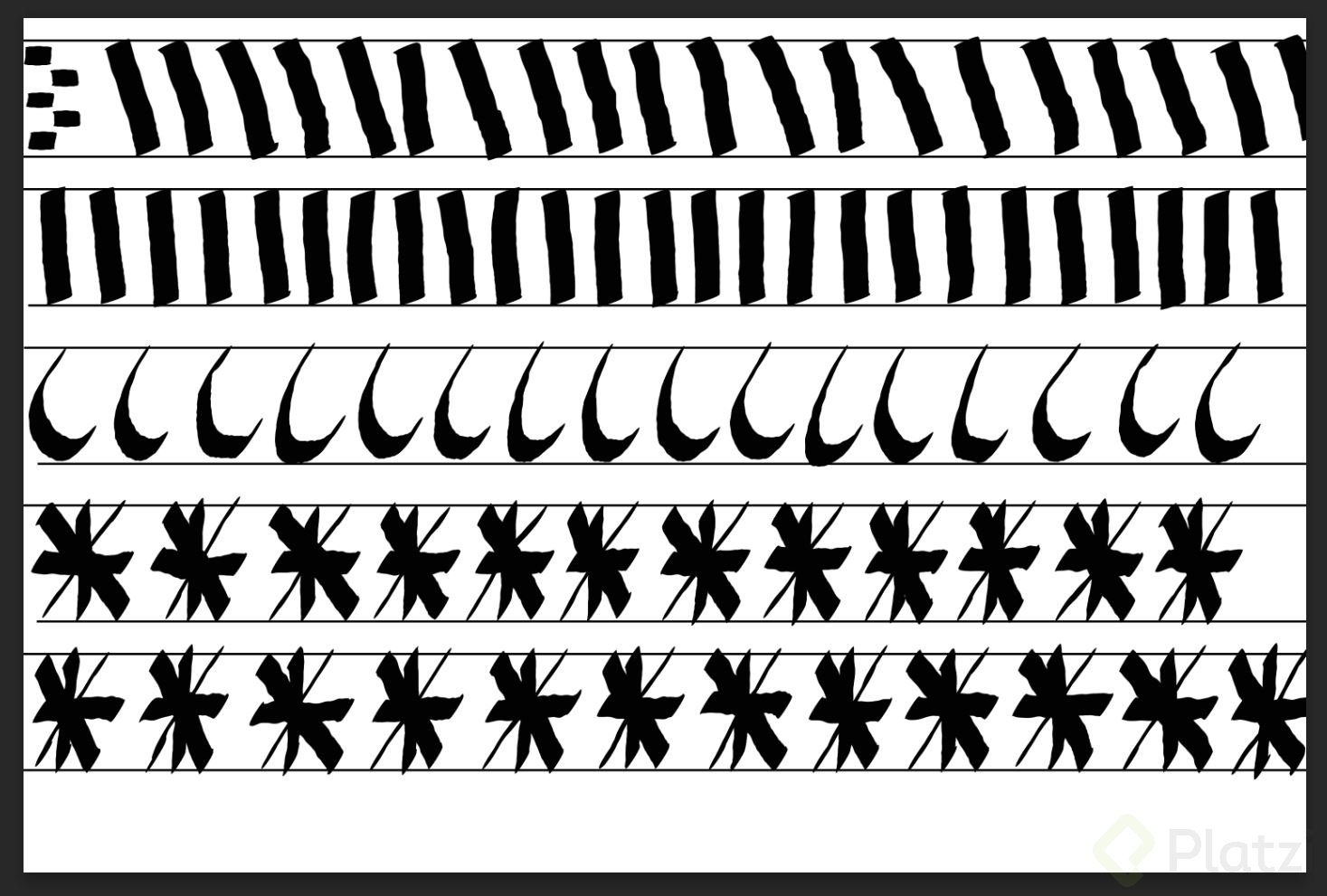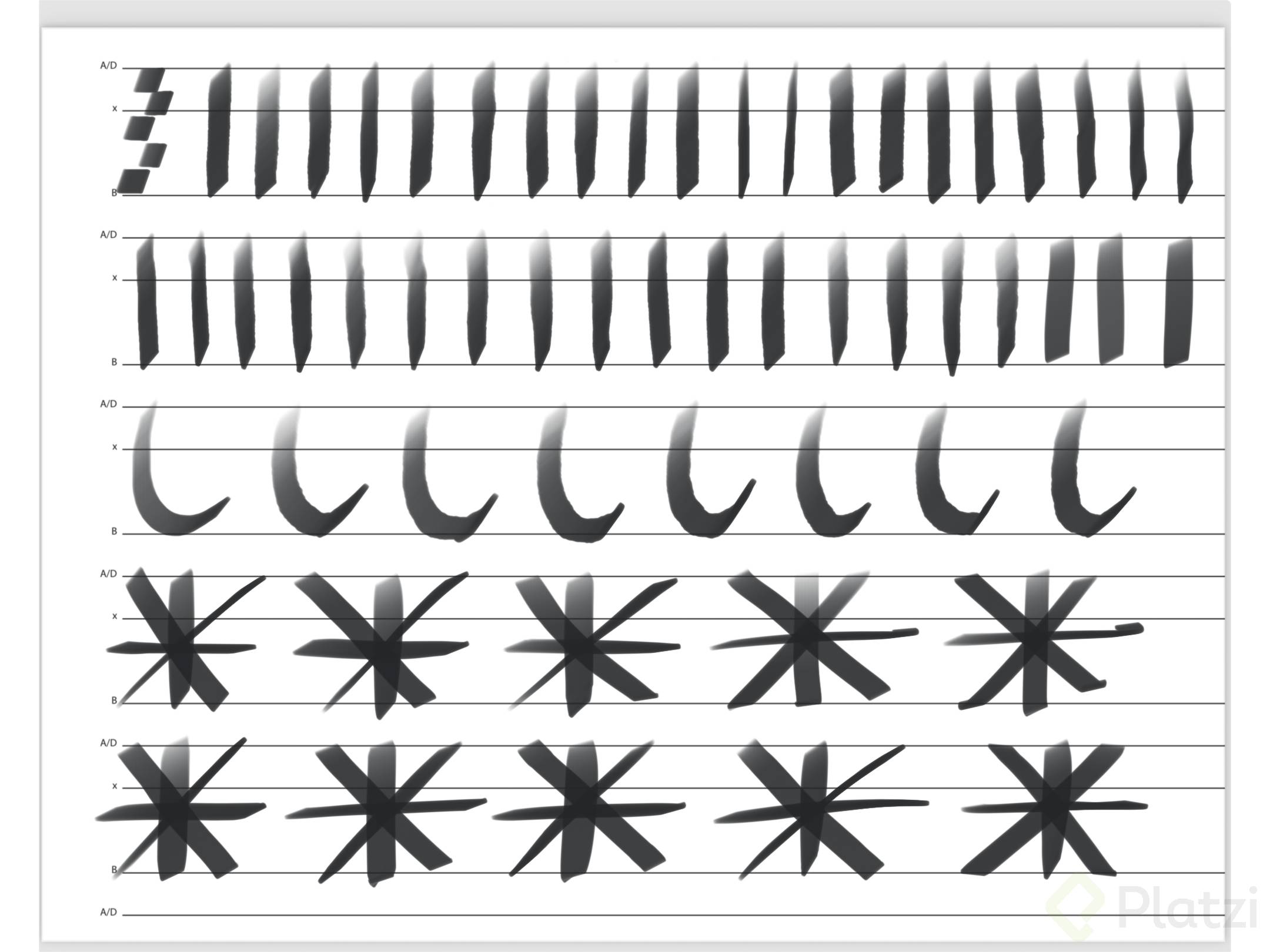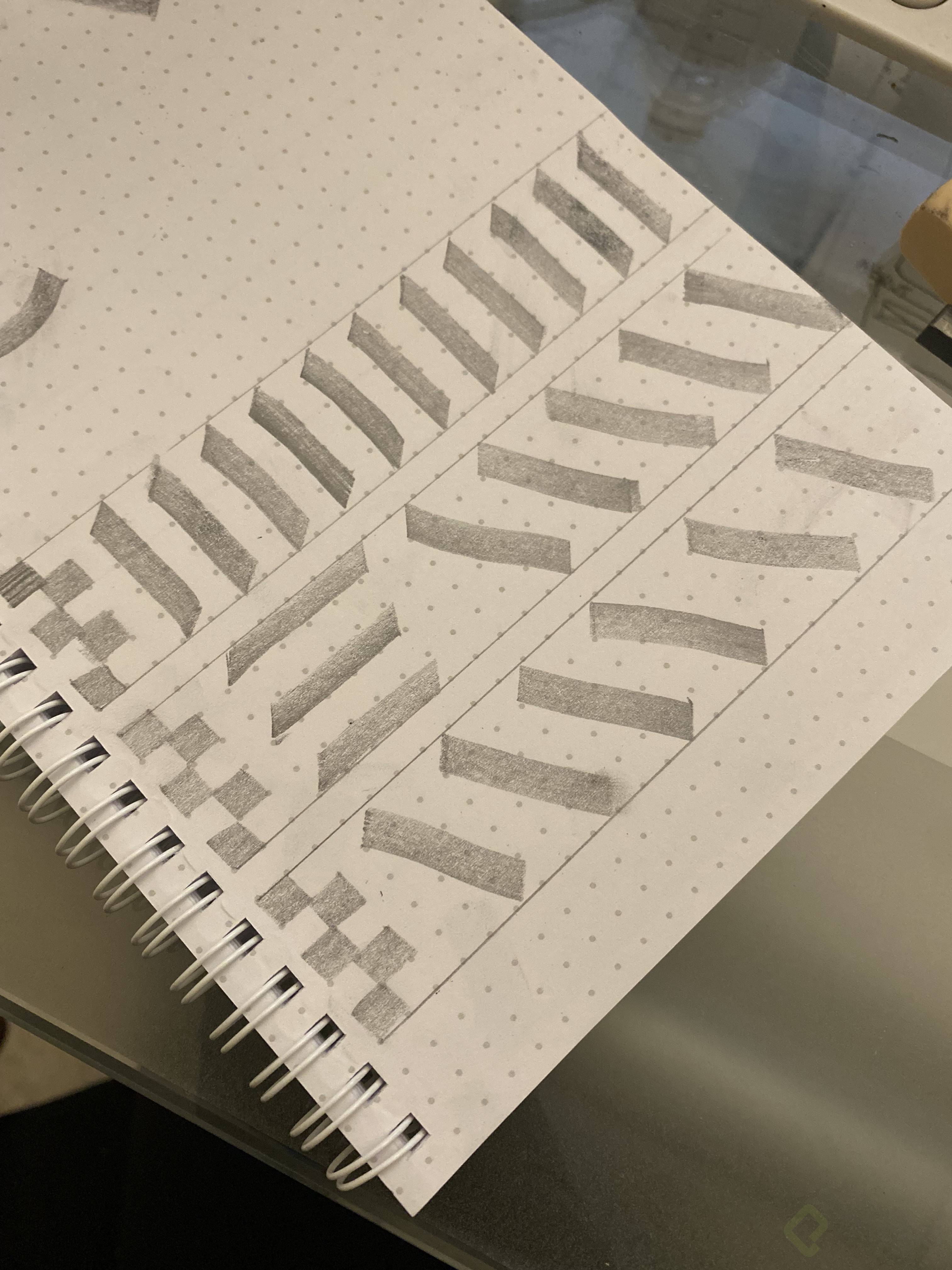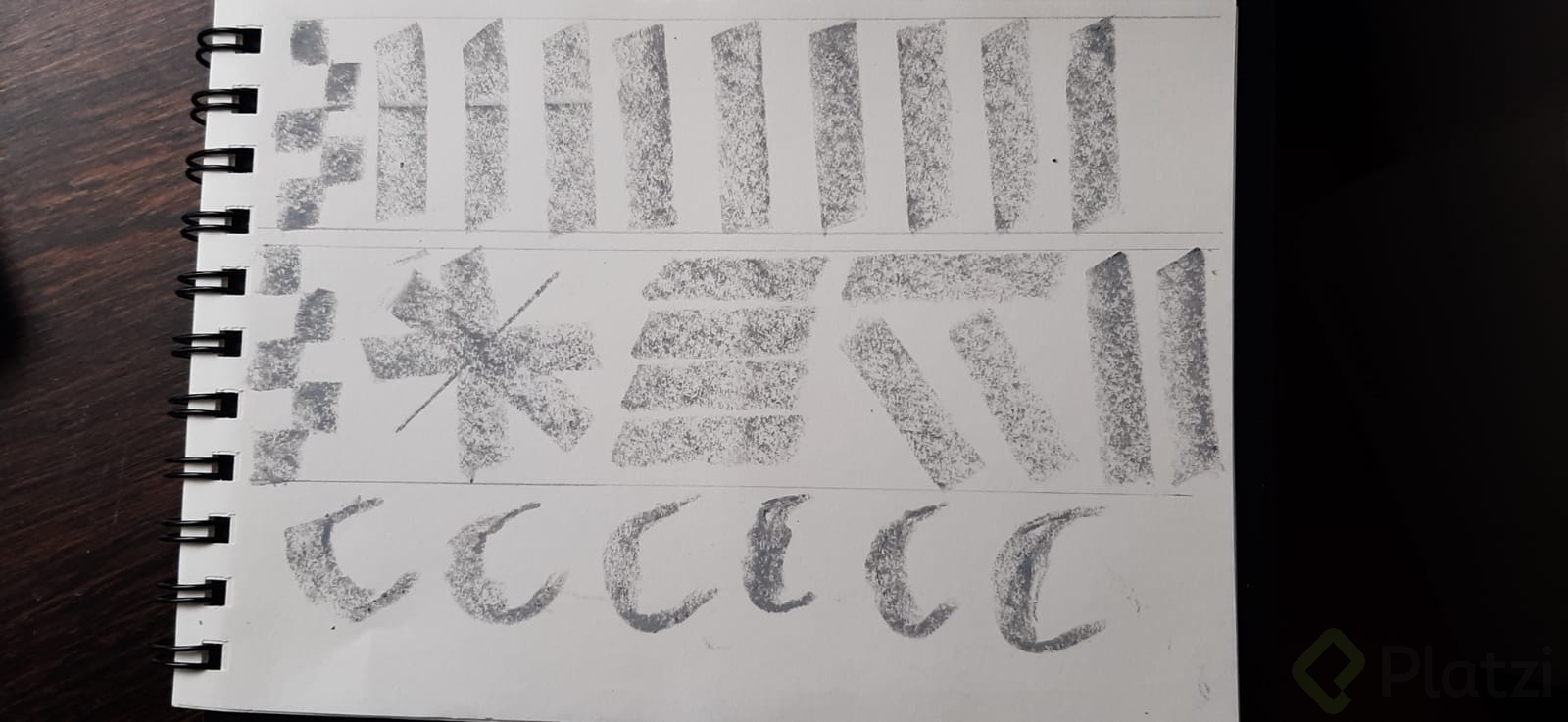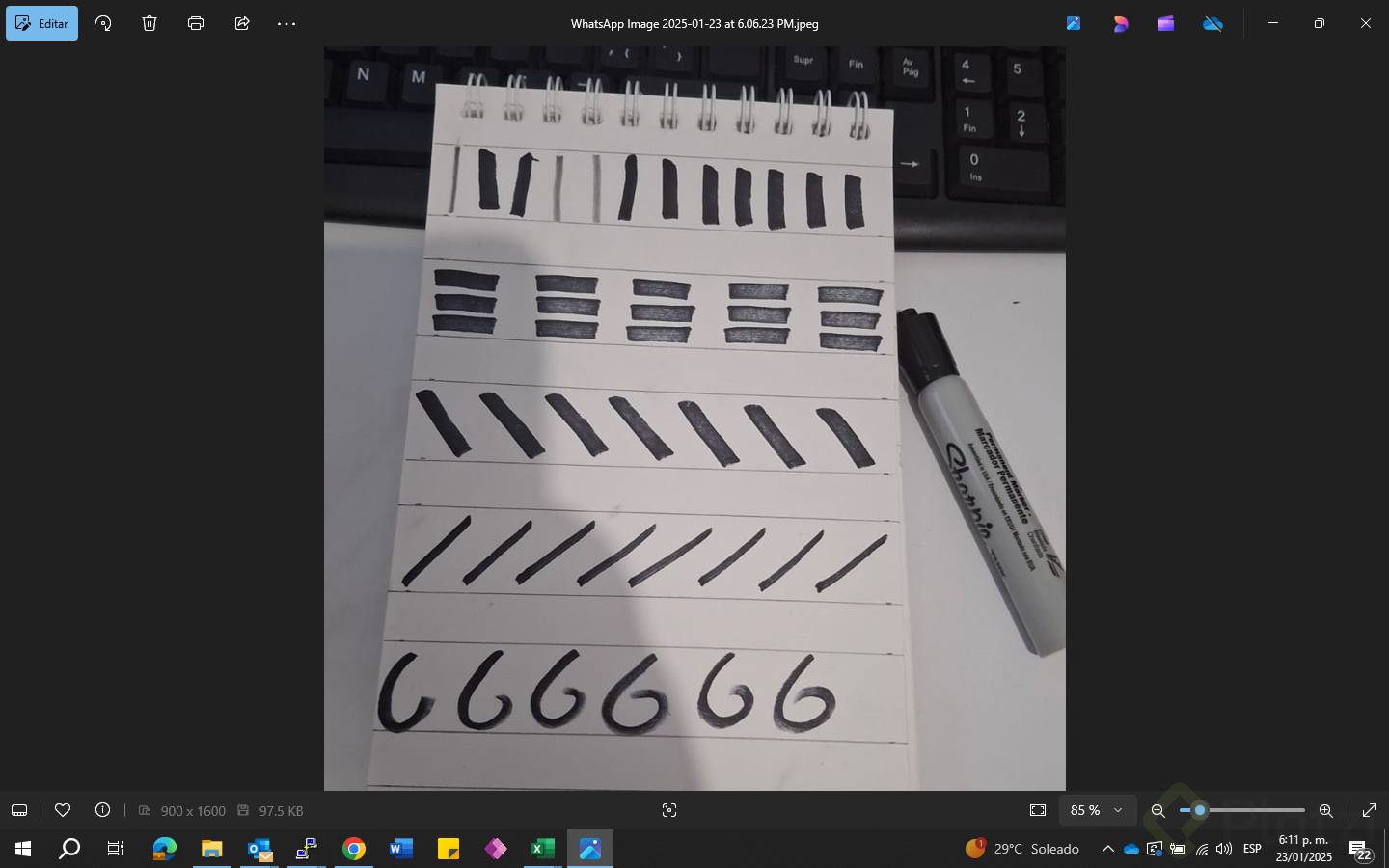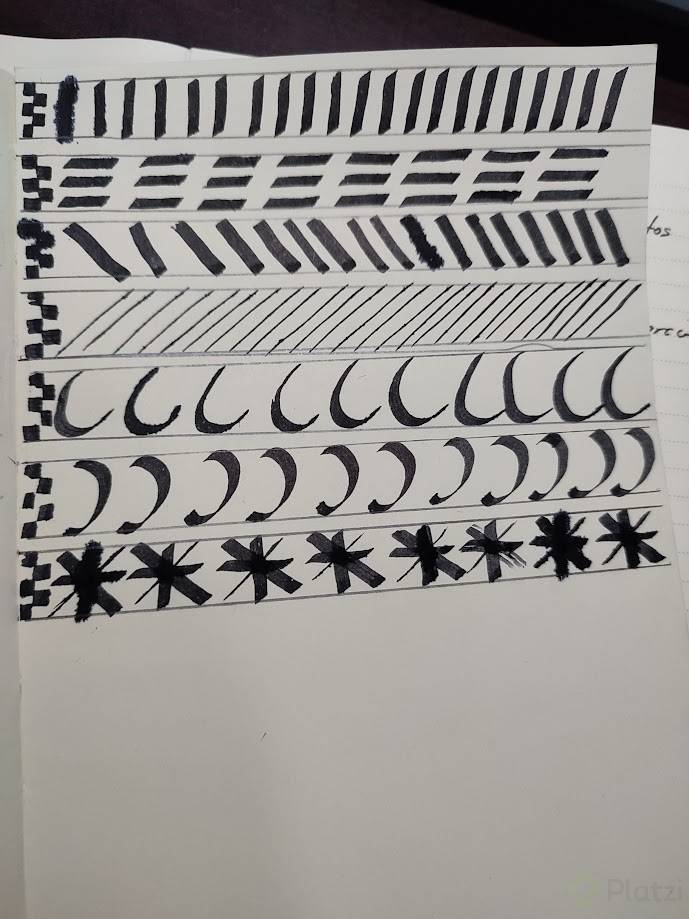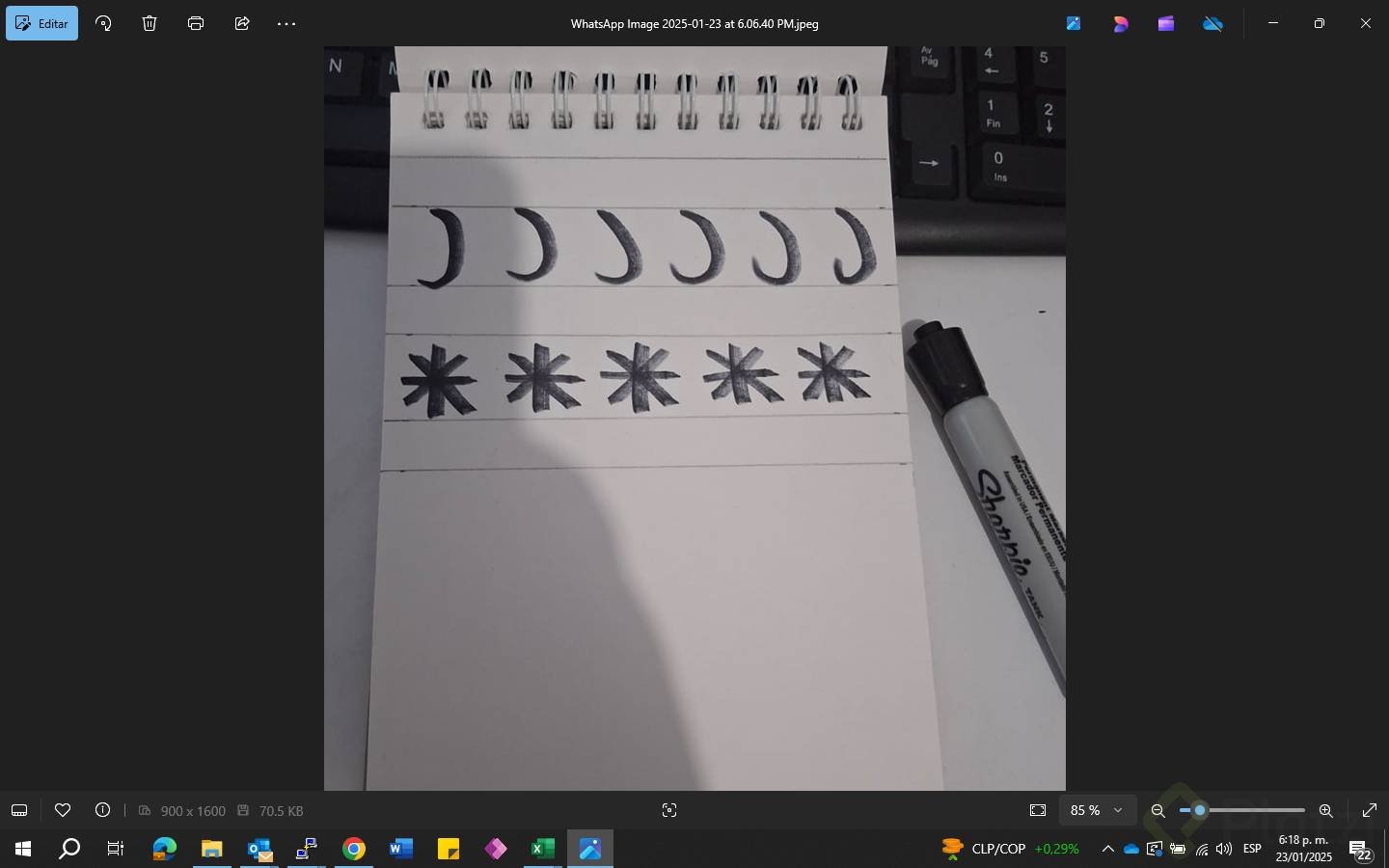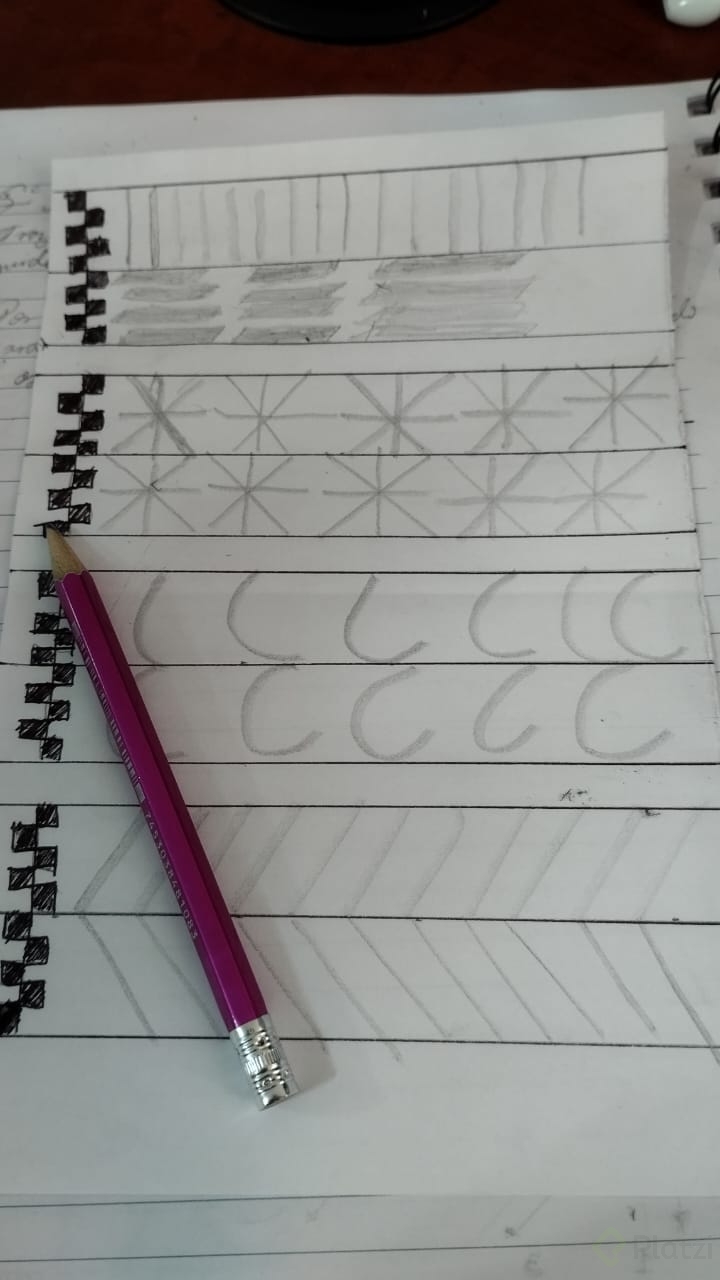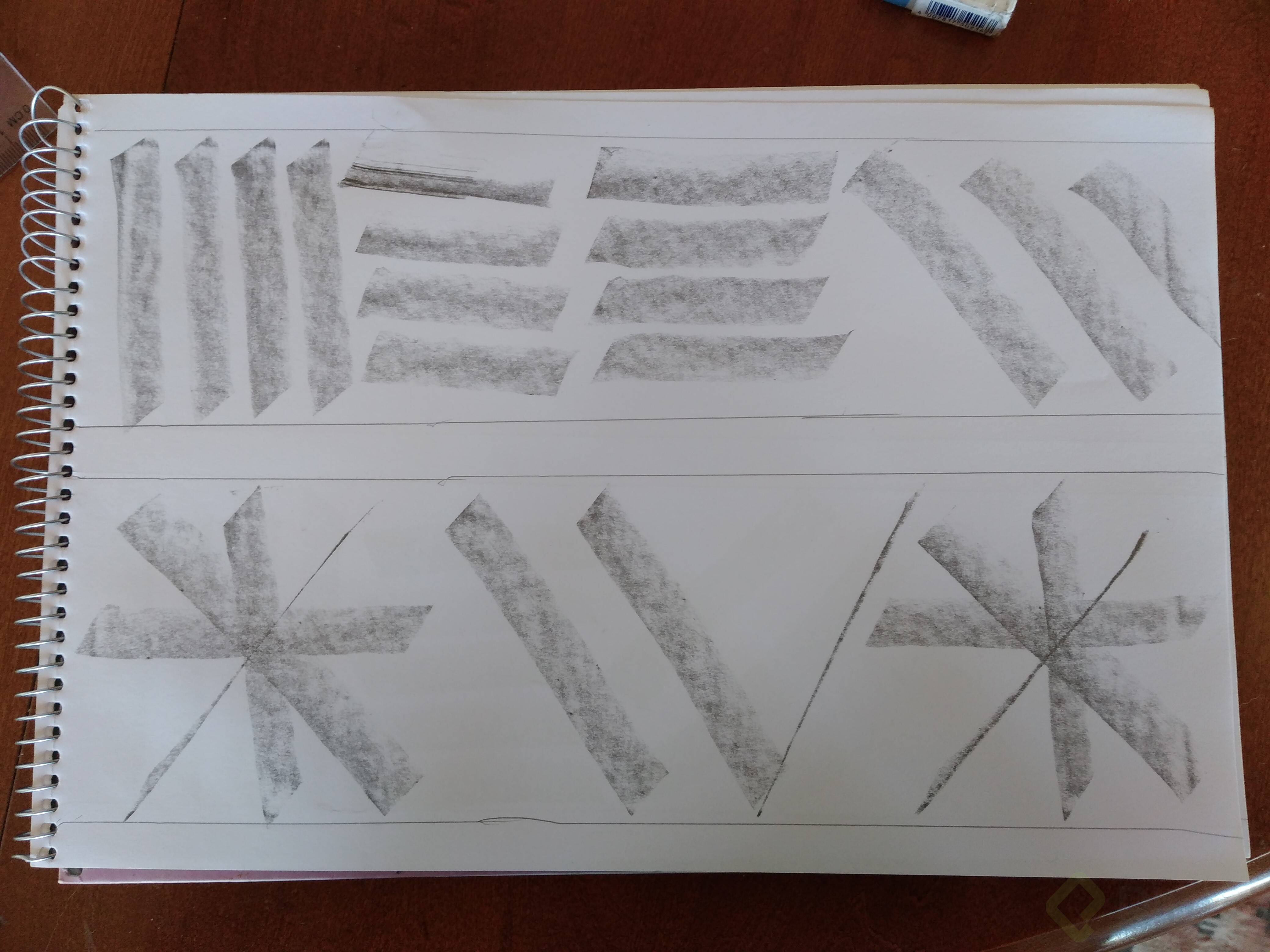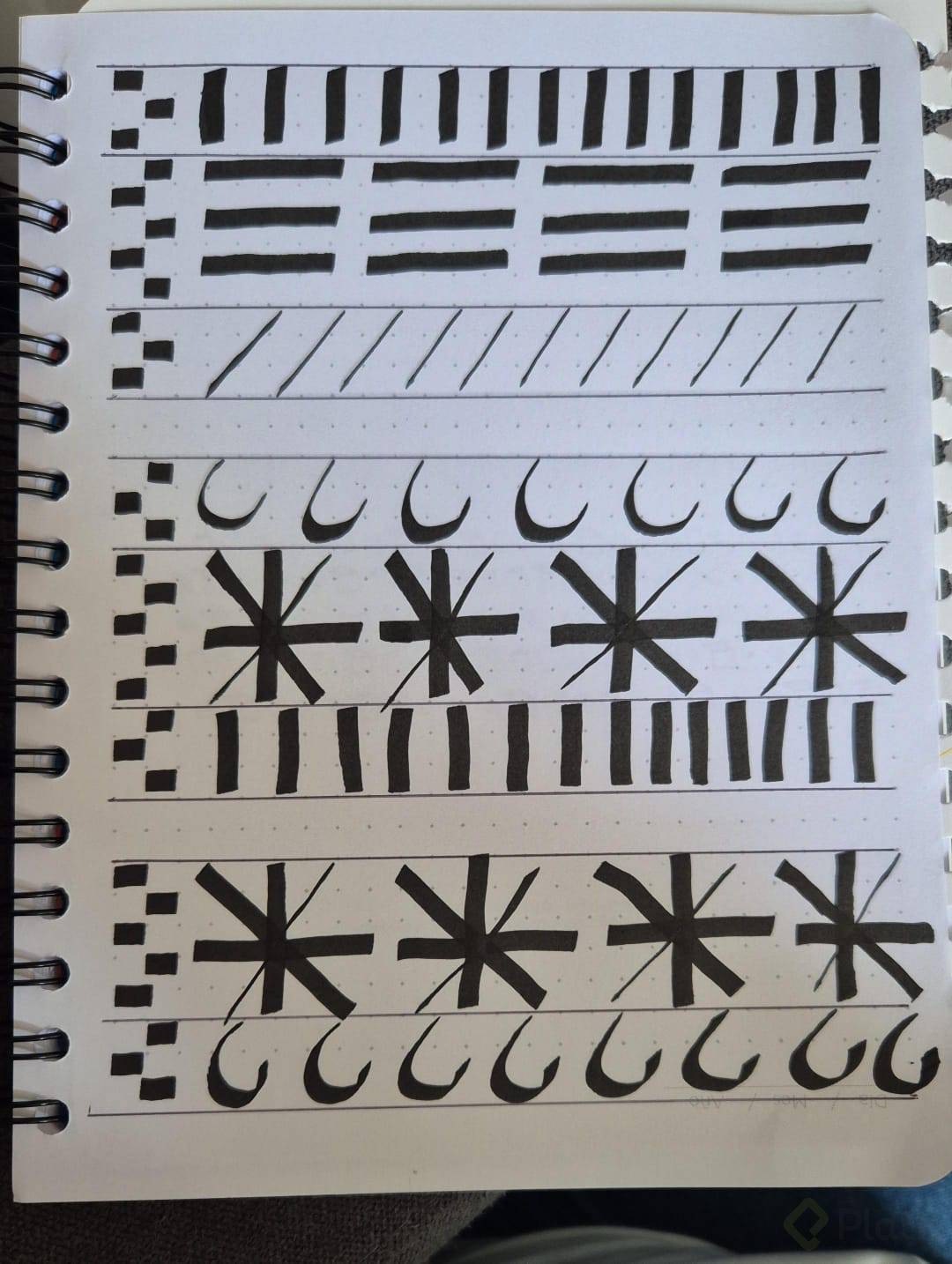
Paso a paso, ejercicios prácticos iniciales
La caligrafía no es solo escribir bonito; es un arte que combina práctica, paciencia y precisión.
Si estás dando tus primeros pasos en este mundo fascinante, es importante comenzar con la disposición correcta de materiales, postura adecuada y técnicas básicas.
Aquí te guío en cómo hacerlo.
1. Posición correcta del papel y la herramienta
La colocación adecuada del papel y el cuerpo facilita el flujo de trazos, especialmente según seas diestro o zurdo:
- Diestros: coloca el papel en la parte inferior derecha de la mesa, inclinado ligeramente hacia la izquierda o derecha según sea más cómodo para ti. Esto evita que tu mano cubra lo que escribes.
- Zurdos: inclina el papel aproximadamente 45 grados hacia la izquierda para reducir el riesgo de manchar el papel con la mano.
Tip: Utiliza un lápiz de grafito bien afilado como herramienta inicial.
Afílalo como un hacha y utiliza lija para obtener una punta fina y uniforme.
2. Definir las alturas en la caligrafía
Establecer alturas es crucial para mantener proporción y consistencia en tus letras.
- Usa un renglón caligráfico como guía.
- Según el maestro Ricardo Rousselot, la altura de la letra "x" debe ser de cinco módulos o panes, estableciendo un sistema de medidas uniforme.
3. Ángulo de inclinación recomendado
El ángulo de inclinación del papel y la herramienta afecta el estilo caligráfico.
- Trabaja con un ángulo de 45 grados como referencia.
- Aunque es difícil mantenerlo siempre, practicar este ángulo garantiza resultados consistentes.
4. Los trazos básicos en caligrafía
Dominar los trazos básicos es esencial antes de avanzar a estilos complejos. Practica los siguientes:
- Trazo vertical: De arriba hacia abajo.
- Trazo horizontal: De izquierda a derecha.
- Trazo diagonal (izquierda a derecha): De abajo hacia arriba o viceversa.
- Trazo diagonal (derecha a izquierda): Igual que el anterior, con sentido inverso.
- Trazo curvo: Permite giros libres, cruciales para letras más fluidas.
5. Cómo practicar los trazos básicos
La práctica repetitiva es la clave para dominar la caligrafía.
Un ejercicio útil es dibujar un asterisco, que incluye todos los tipos de trazos básicos.
Este ejercicio:
- Mejora tu coordinación mano-ojo.
- Te ayuda a reconocer ritmo, altura, color y proporción en las letras.
6. Alineación y alturas
Asegúrate de que tus trazos básicos toquen tanto el "techo" como el "piso" del renglón caligráfico.
Esto garantiza:
- Letras alineadas.
- Un aspecto uniforme en tus composiciones.
Ejemplo del ejercicio realizado en Photoshop con un pincel por el estudiante Haber Alexander Barinas Vega.
La constancia es tu mejor aliada en este hermoso arte. ¡Sigue explorando y mejorando cada día!